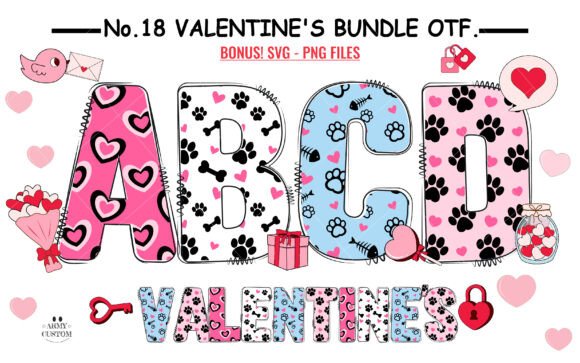
Love Valentine's Army Bundle
Jika anda sedang mencari aset berkualiti tinggi seperti Love Valentine's Army Bundle, pakej premium ini merupakan pilihan yang hebat untuk projek kreatif anda.
Dicipta dengan ketepatan, Love Valentine's Army Bundle menyediakan vektor yang bersih, tipografi yang licin dan lesen komersial untuk ketenangan fikiran.
Sama ada anda mencipta produk POD (Print on Demand), jemputan perkahwinan atau grafik media sosial, Love Valentine's Army Bundle amat bersesuaian.